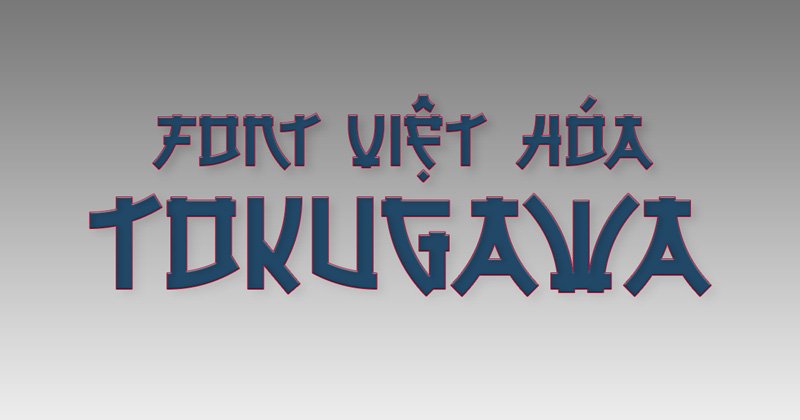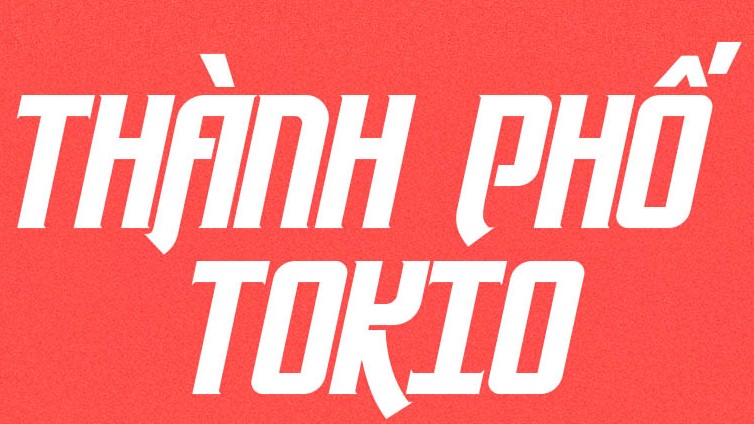
Font chữ Nhật Bản là nguồn tài nguyên đồ họa không thể thiếu khi bạn thực hiện các dự án thiết kế bao bì hàng xuất khẩu, nhận diện thương hiệu cho nhà hàng Nhật Bản hoặc các sản phẩm mang đậm phong cách văn hóa xứ Phù Tang. Trong thiết kế đồ họa hiện đại, nhóm phông chữ này bao gồm cả hệ chữ tượng hình bản địa (Kanji, Kana) và các dòng Font chữ kiểu Nhật Bản Việt hóa được cách điệu trên nền chữ cái Latinh để gõ tiếng Việt nhưng vẫn giữ trọn vẹn tinh thần tối giản (Zen) hoặc nét cọ thư pháp (Shodo). Doozypack.vn cung cấp link tải trọn bộ Font chữ Nhật Bản Full chuẩn kỹ thuật, giúp bạn sở hữu kho phông chữ đẳng cấp mà không lo gặp bất kỳ lỗi hiển thị dấu thanh nào khi thiết kế in ấn.
Phân loại các nhóm font chữ Nhật Bản phổ biến nhất
Trước khi bắt đầu sử dụng, bạn cần xác định rõ mục đích thiết kế để lựa chọn đúng nhóm phông chữ phù hợp với yêu cầu thực tế của sản phẩm.
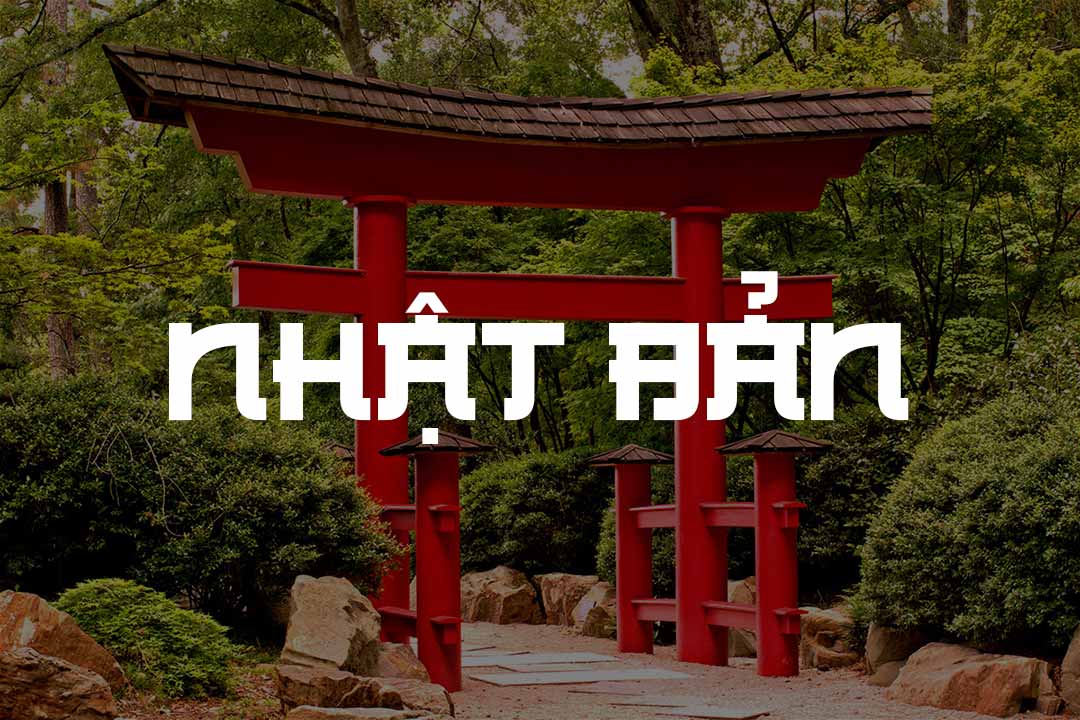
Font chữ tiếng Nhật bản địa chuẩn (Kanji, Kana)
Đây là nhóm phông chữ phục vụ trực tiếp cho việc hiển thị ngôn ngữ tiếng Nhật gồm ba bảng chữ cái: Kanji, Hiragana và Katakana. Việc sử dụng đúng các bộ Font chữ tiếng Thái Lan hay tiếng Nhật bản địa là bắt buộc khi in ấn tem nhãn phụ, thông số kỹ thuật cho các mặt hàng điện tử, mỹ phẩm hoặc thực phẩm nhập khẩu trực tiếp từ Nhật Bản để tuân thủ quy chuẩn pháp lý xuất nhập khẩu.
Font chữ kiểu Nhật Bản Việt hóa mang đậm chất Zen & Anime
Nếu bạn đang tìm kiếm Font chữ Nhật Bản đẹp để làm logo nhà hàng Sushi, bao bì bột trà xanh Matcha hoặc poster sự kiện Manga/Anime, nhóm Font chữ phong cách Nhật Bản Việt hóa là giải pháp hoàn hảo. Đây là các ký tự tiếng Việt nhưng được các nhà thiết kế thổi hồn vào đó thông qua các đường nét hình học tối giản (giống phong cách kiến trúc Zen) hoặc các nhát cọ thư pháp sắc sảo.
Đặc điểm thẩm mỹ của phông chữ phong cách Nhật Bản
Sức hút của các bộ Font chữ kiểu Nhật Bản Việt hóa nằm ở sự giao thoa tinh tế giữa truyền thống tối cổ và tư duy thiết kế đương đại.
- Tinh thần tối giản (Zen Minimalism): Các dòng Sans-serif phong cách Nhật thường có cấu trúc vô cùng sạch sẽ, khoảng trắng (space) rộng rãi, mang lại cảm giác tĩnh tại, an yên và sang trọng.
- Nét cọ thư pháp Shodo uy nghi: Các dòng Display phong cách Nhật mô phỏng lại nhát chém kiếm Katakana hoặc nét cọ lông dẹt, tạo ra sức nặng thị giác cực kỳ mạnh mẽ cho các tiêu đề chính.
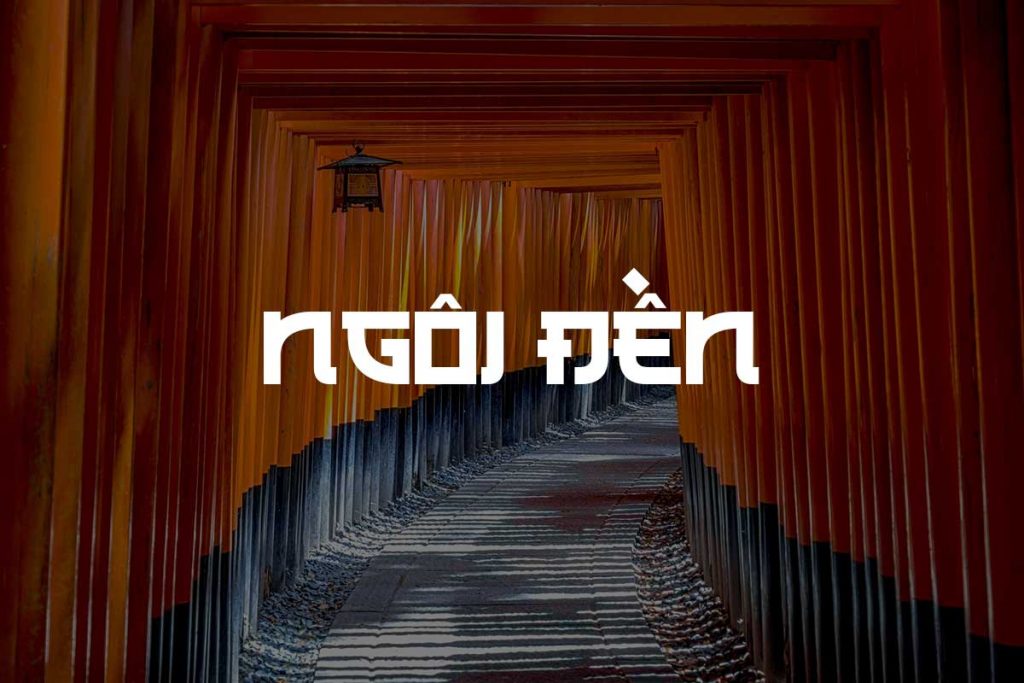
03 Ứng dụng thực tế của font chữ Nhật Bản trong sản xuất bao bì
- Bao bì Bột Matcha & Trà xanh: Tiêu đề thương hiệu in bằng font phong cách Nhật kết hợp cùng chất liệu giấy Kraft nâu hoặc giấy mỹ thuật nhám, tạo nên phong cách mộc mạc, lành tính và đậm đà phong vị xứ Phù Tang.
- Hộp giấy đựng Sushi & Đồ ăn Takeaway: Sử dụng phông chữ Nhật Bản cho hộp đựng thực phẩm mang lại cảm giác sạch sẽ, cao cấp và chuyên nghiệp cho các chuỗi nhà hàng.
- Tem nhãn dán Mỹ phẩm Nhật Bản: Cấu trúc chữ tối giản giúp các thông tin chi tiết trên nhãn dán chai lọ trở nên minh bạch và cực kỳ sang trọng.
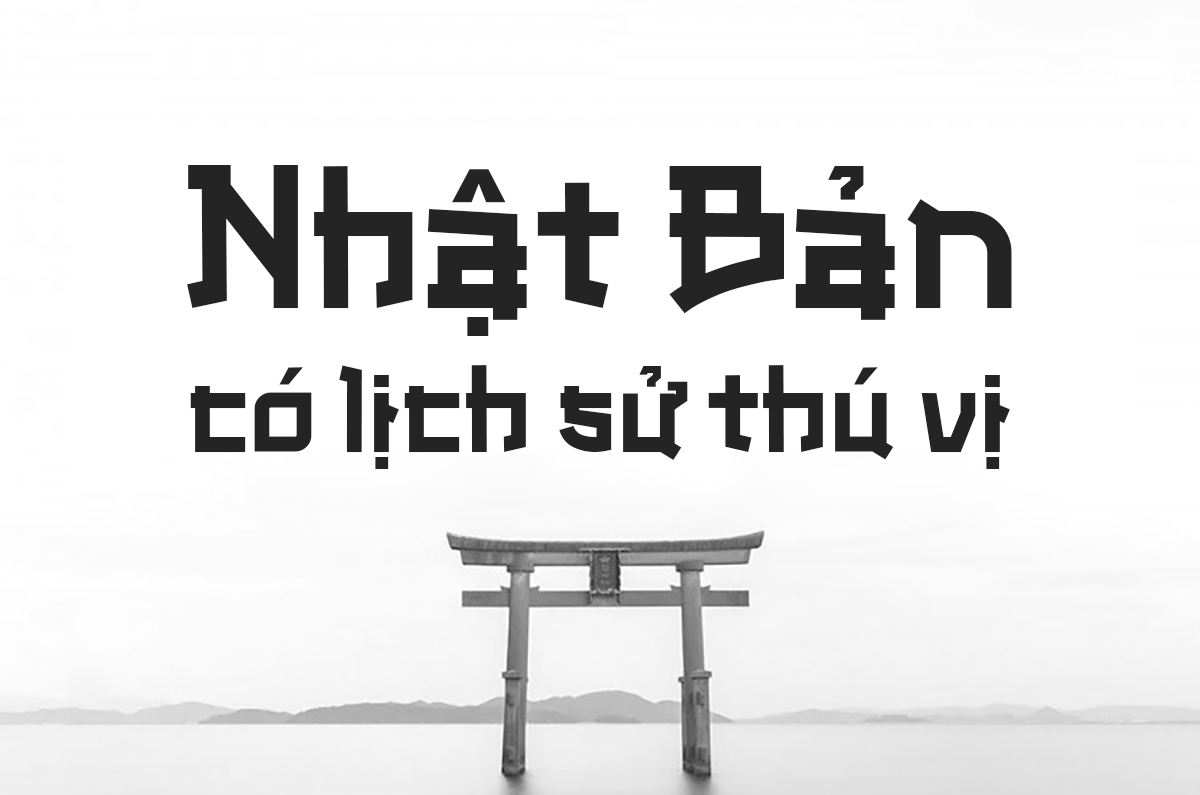
Lưu ý kỹ thuật khi in ấn với phông chữ phong cách Nhật
- Kiểm soát độ dày nét khi in kích thước nhỏ: Các Font chữ Nhật Bản đẹp thường có các biến thể nét mảnh (Light). Khi in trên giấy có độ thấm mực nhanh như giấy Kraft, bạn nên để size chữ tiêu đề tối thiểu từ 9pt trở lên để bảo đảm độ rõ nét.
- Gia công ép kim vàng (Hot Stamping): Nhờ cấu trúc hình học dứt khoát, các font phong cách Nhật cực kỳ phù hợp cho kỹ thuật ép kim nhũ vàng hoặc nhũ bạc trên nắp hộp quà tặng, tạo hiệu ứng phản quang tinh tế.